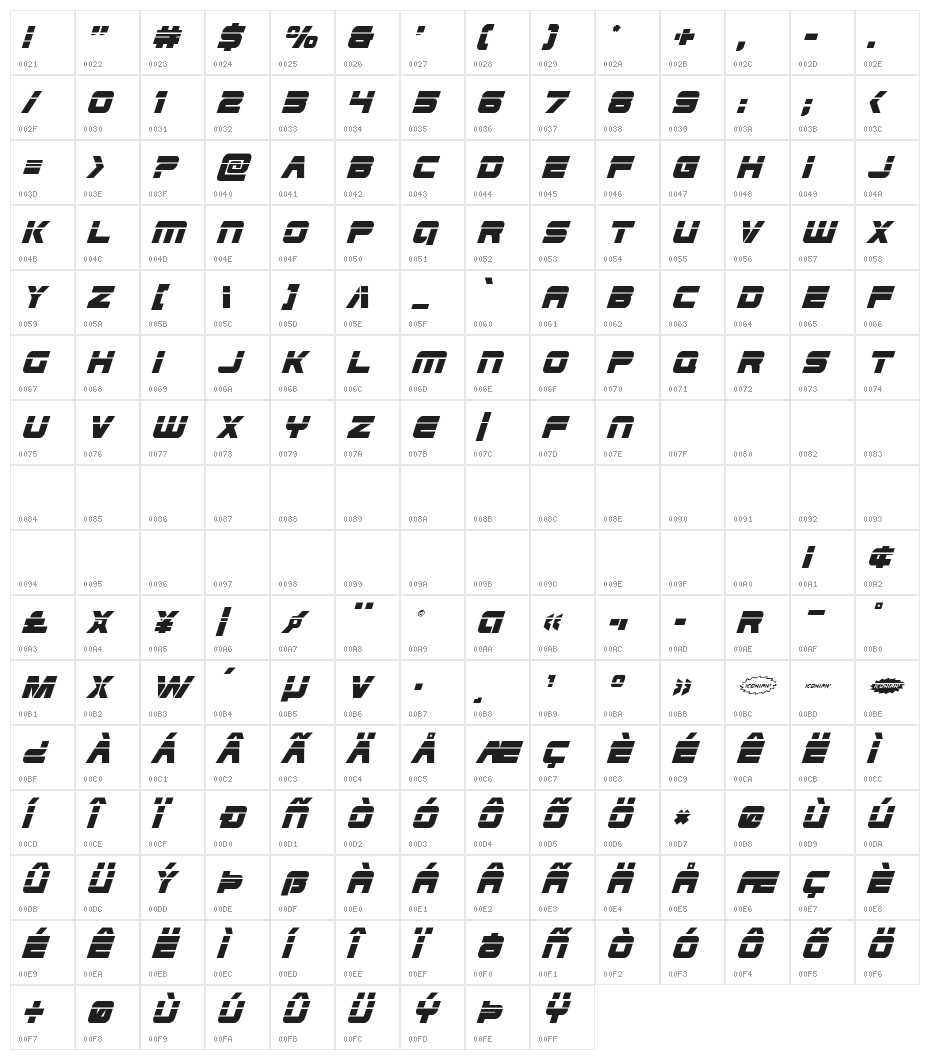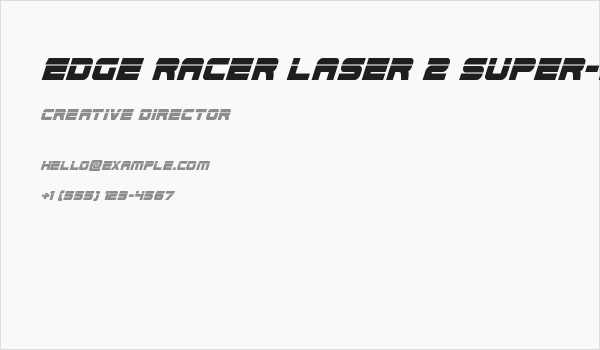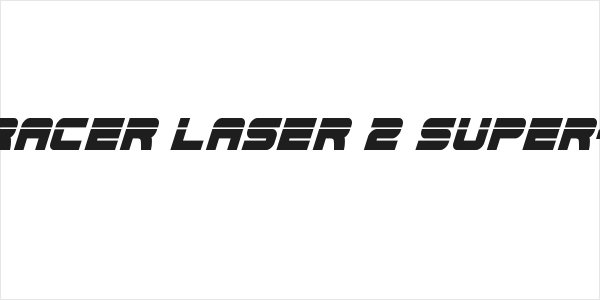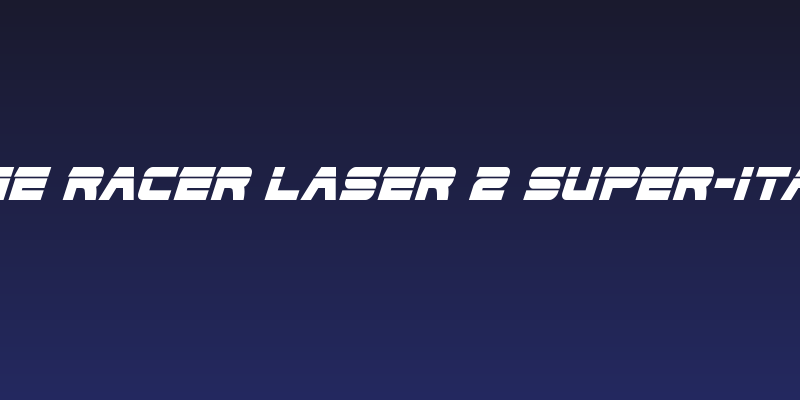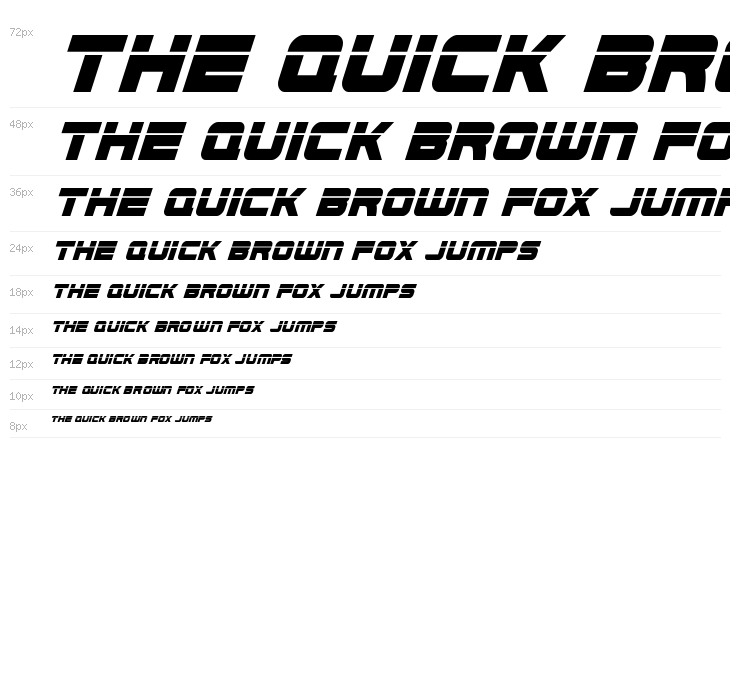
Edge Racer Laser 2 Super-Italic Font
| Progetti proposti | Ideal for sports branding, automotive designs, video game titles, and dynamic advertising campaigns. |